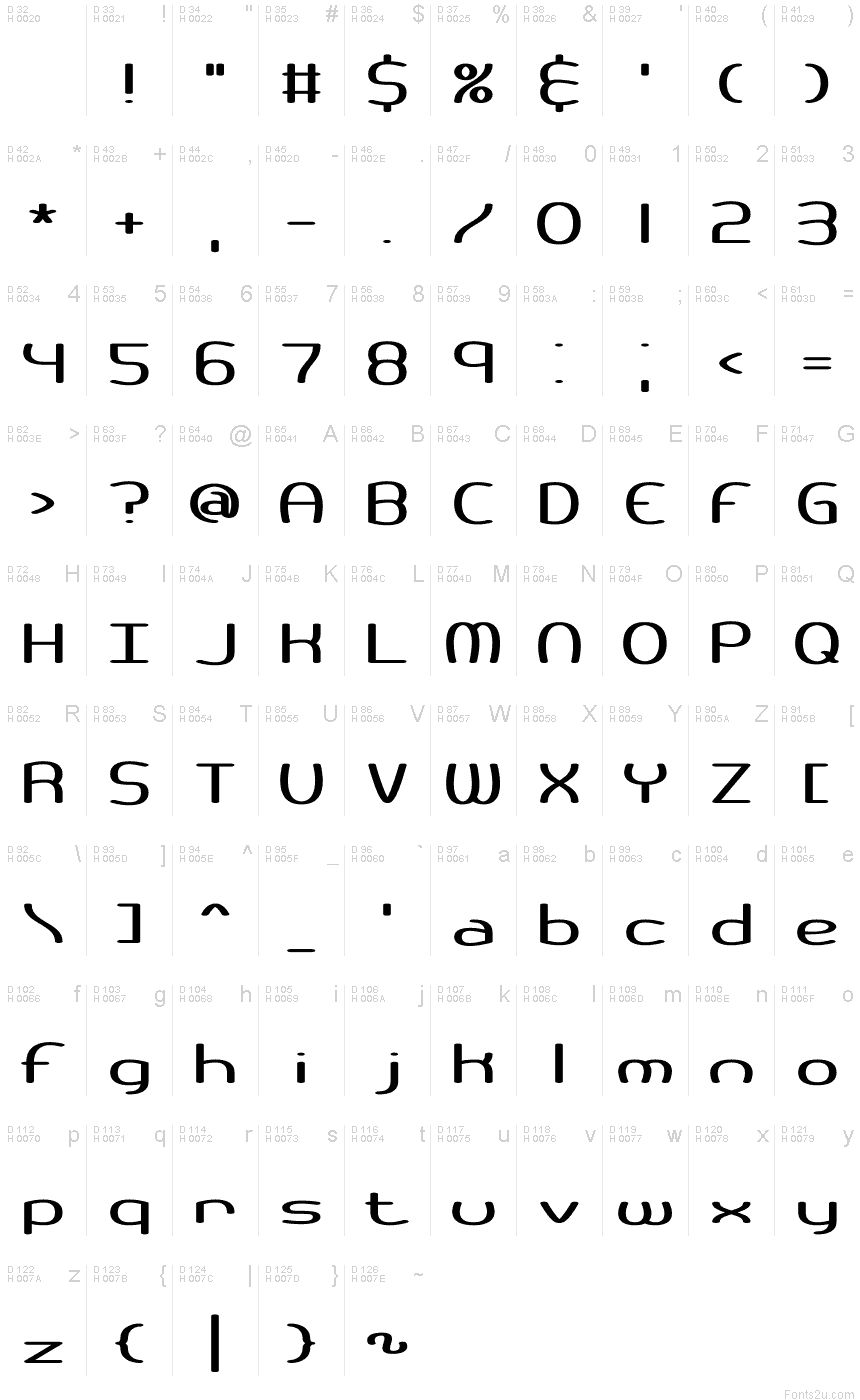
Pneumatics Wide BRK od AEnigma Fonts to darmowy, zaokrąglony font techno typu display o miękkim, napowietrzonym wyglądzie. Litery wyglądają, jakby zostały rozciągnięte z rurek, a nie narysowane ostrymi krawędziami; charakteryzują się szerokimi łukami, niskim kontrastem i zwartym, futurystycznym rytmem, który jest raczej zabawny niż surowy.
Dzięki temu ten darmowy font naturalnie pasuje do okładek albumów, ulotek klubowych, brandingów w stylu retro-futurystycznym, nagłówków plakatów i plansz tytułowych, wszędzie tam, gdzie potrzebny jest ruch bez agresji. Sprawdza się również w krótkich logotypach i hasłach na okładkach, ponieważ napuchnięte krzywe i wąskie łączenia nadają nawet krótkim słowom wyporną, niemal unoszącą się w powietrzu formę.